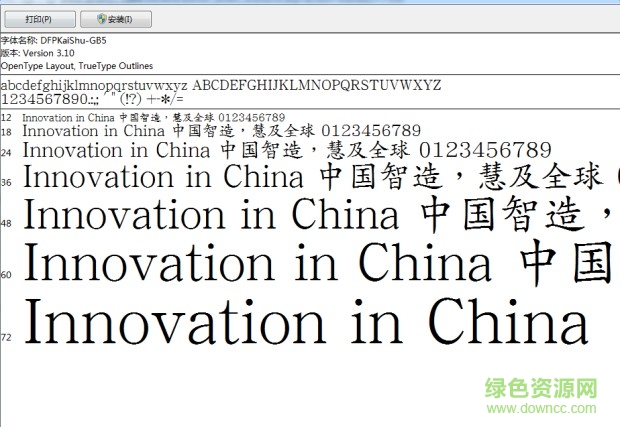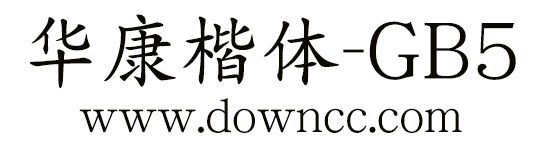
華康楷體-GB5
華康楷體-GB5字體華康字體庫里的一款字體,該字體屬于藝術(shù)設(shè)計方面的字體,筆勢雄奇,姿態(tài)橫生。適合用于廣告設(shè)計、雜志報刊等領(lǐng)域。有喜歡的朋友趕快來綠色資源網(wǎng)下載使用吧!
華康開頭GB5預(yù)覽圖:
華康楷體GB5字體